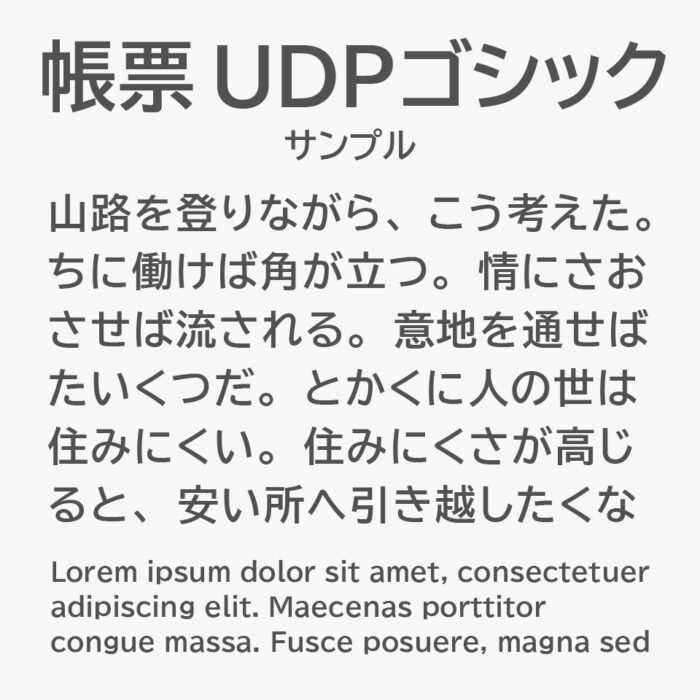
帳票 UDPゴシック (FORM UDPGothic)フォントは、「BIZ UDPゴシック」の「1」と「1(全角)」の幅のみを変更し、数字(0〜9)を等幅に調整されたゴシック体フォントです。
「BIZ UDPゴシック」を使いたいが数字は等幅にしたい、等幅の「BIZ UDゴシック」だと数字が細すぎる、といった声もあり、そんなユーザーのために調整されたフォントです。